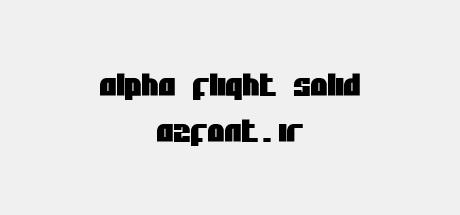
Alpha Flight Solid
فونت زیبای رایگان Alpha Flight Solid
قلم زیبای Alpha Flight Solid از سری قلم های بسیار زیبا برای تایپوگرافی و لوگو تایپ می باشد.این قلم در وزن Regular و توسط saud_10@live.com طراحی و منتشر شده است.
Influenced by a C64 AFL logo painted by RRR.